Keilschrift
Im Zweistromland zwischen Euphrat und Tigris entsteht vor mehr als 5000 Jahren die älteste uns bekannte Schrift. Mit dem Griffel wird sie als Folge keilförmiger Eindrücke in weichen Ton gepresst — Verwaltungstexte, Gesetze und Mythen bewahrt sie für die Nachwelt.
Zweistromland
Schrift im weichen Ton
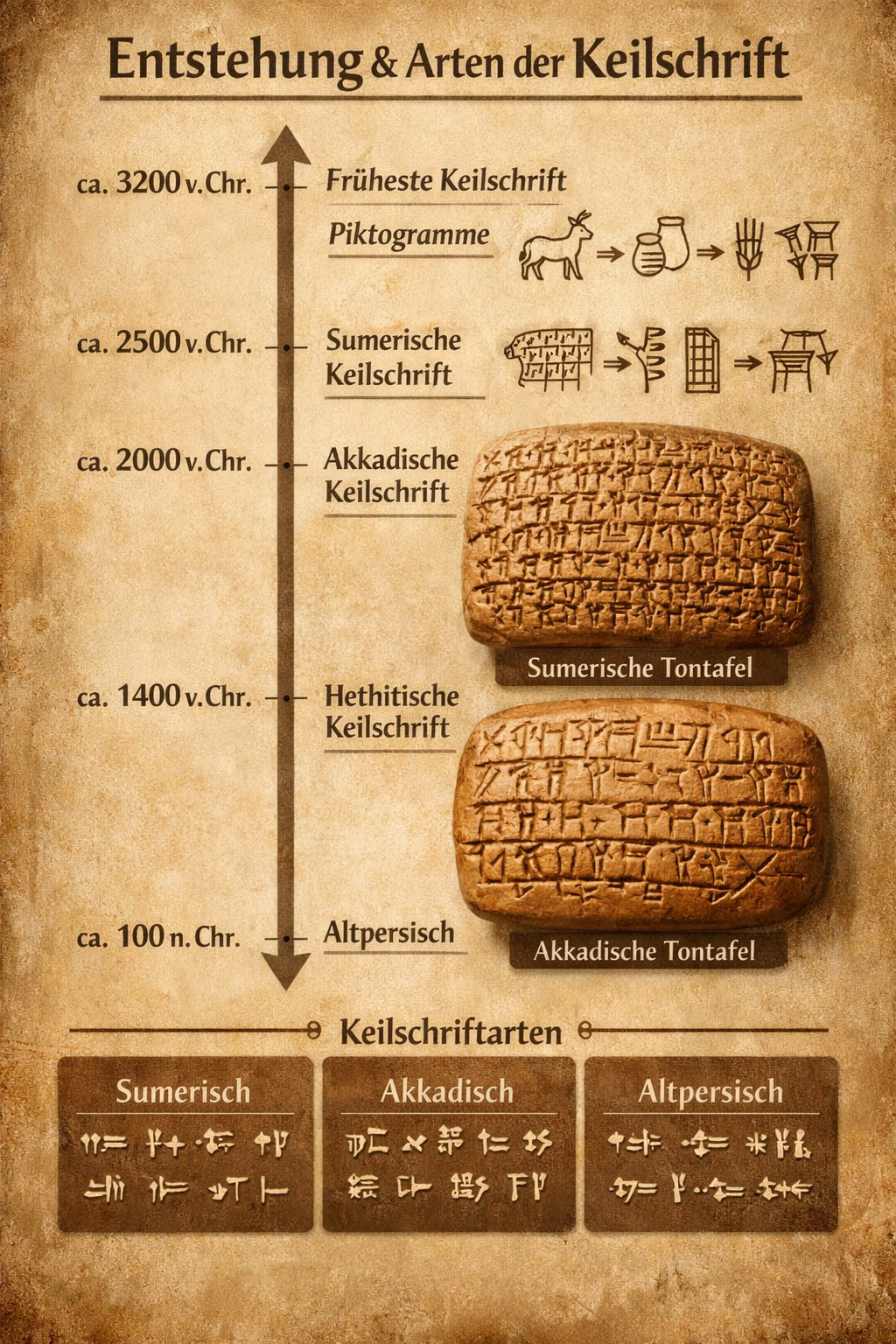
Um 3000 v. Chr.
Tontafel und Griffel
Aus zunächst piktografischen Zeichen entwickelt sich die Keilschrift zu einem komplexen System aus Silben- und Wortzeichen. Auf gebrannten Tontafeln überdauert sie Jahrtausende — eine der robustesten Schriftträger der Menschheit.
Sumer & Babylon
Der sumerische Schreiber
Schreiber waren in Mesopotamien eine angesehene Berufsgruppe. In Tempelschulen lernten sie hunderte Zeichen, verwalteten Vorräte, schrieben Verträge und überlieferten epische Erzählungen wie das Gilgamesch-Epos.